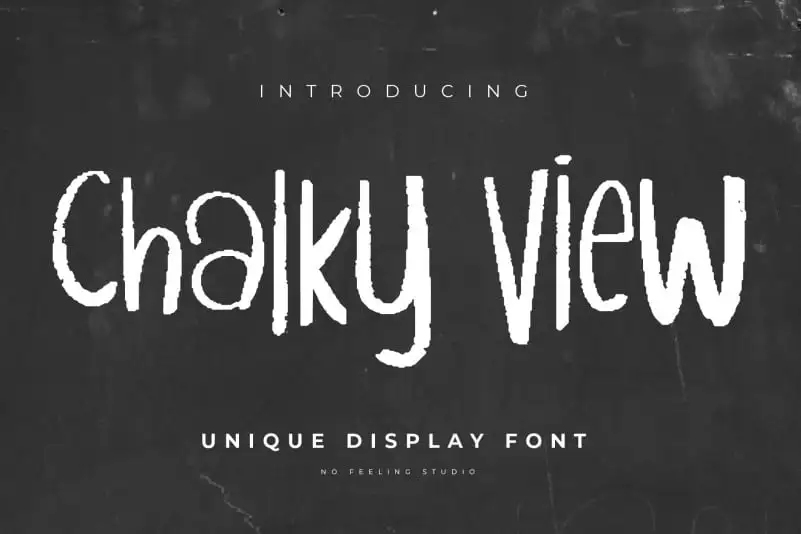
Chalky View Display Font – Download Grátis
A Chalky View Display Font é uma escolha perfeita para quem busca trazer vida e originalidade a seus projetos de design. Inspirada no gosto natural do esmalte de cera aplicado na grade de um salão de aula, esta fonte carrega consigo uma sensação acolhedora de textura de papel branco sujo. Com o seu estilo de escrita raspada e o toque delicado do próprio material usado para escrever, ela adiciona um toque único e encantador ao seu design. Este é mais que simplesmente uma fonte; ele transforma seus projetos em algo autêntico e atraente. Seja para rótulos de livros escolares antigos ou capas de jornal vintage, esta Chalky View Display Font vai adicionar o toque perfeito à sua arte digital.
Designer: No Feelings Studio